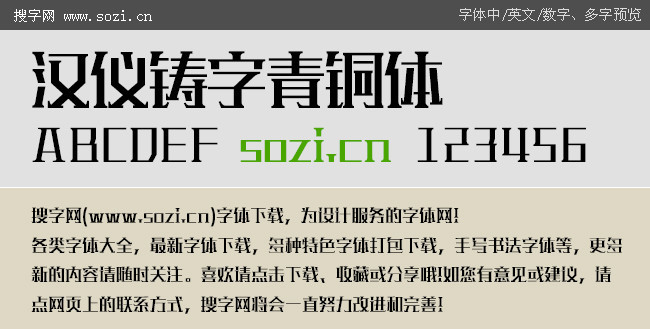
漢儀鑄字青銅體
搜字網(wǎng)給大家提供一款漢儀鑄字青銅體中文字體下載,漢儀鑄字青銅體完美的將青銅藝術(shù)跟字體進(jìn)行融合,在字型筆畫(huà)方面也是完美的展現(xiàn)了青銅器的特點(diǎn),適用于畫(huà)冊(cè)設(shè)計(jì)、海報(bào)設(shè)計(jì)、包裝設(shè)計(jì)等場(chǎng)合使用。(本字體為個(gè)人非商用版,如需要商用請(qǐng)聯(lián)系漢儀公司購(gòu)買(mǎi)版權(quán))